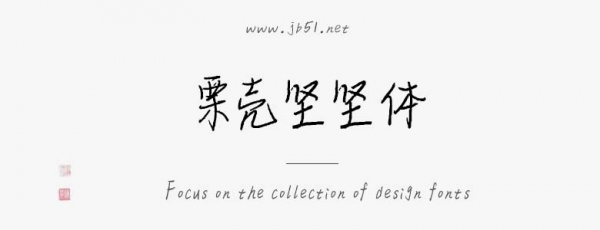
栗殼堅(jiān)堅(jiān)體是由栗殼字庫出品的字體,這款字體筆觸纖細(xì),書寫流暢,具有很好的視覺感,適合應(yīng)用于藝術(shù)設(shè)計(jì)、平面宣傳設(shè)計(jì)、網(wǎng)頁設(shè)計(jì),書法字帖等領(lǐng)域,需要的朋友可以前來本站下載。